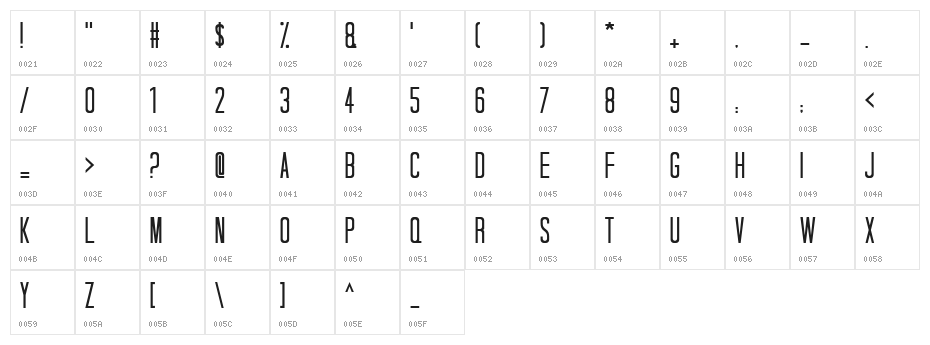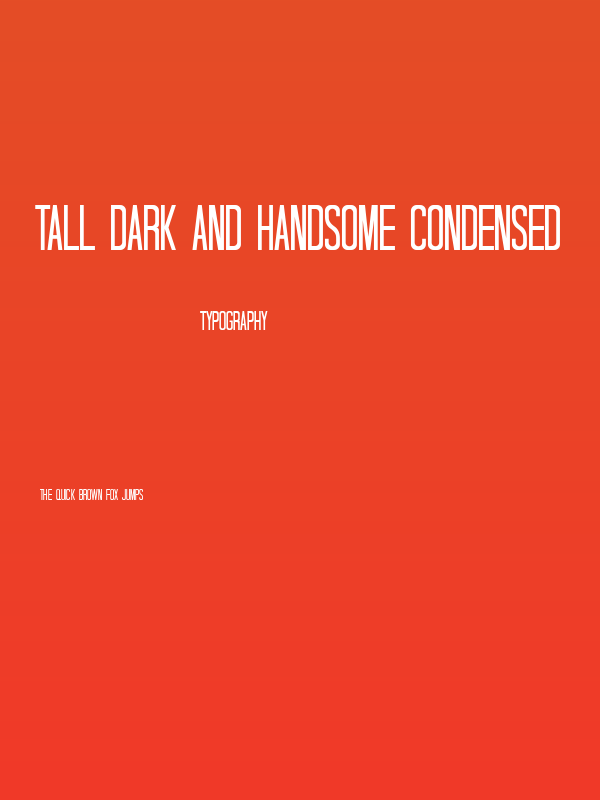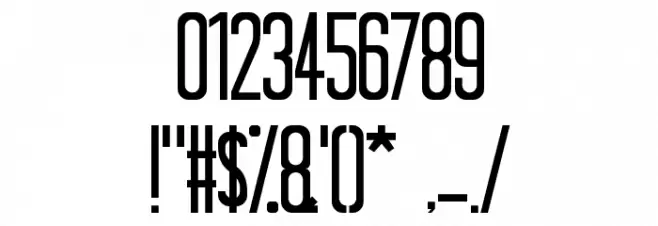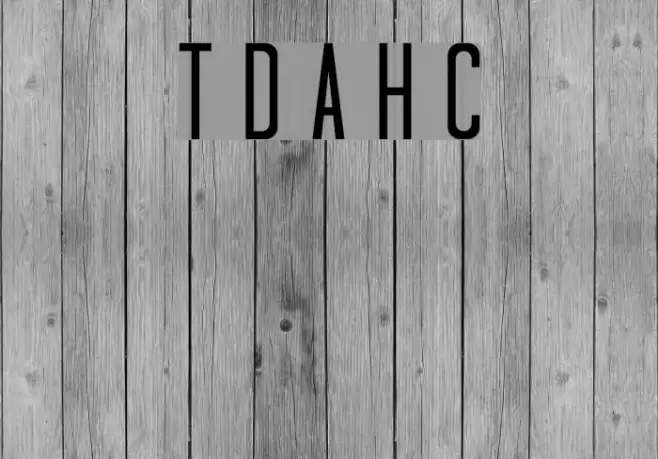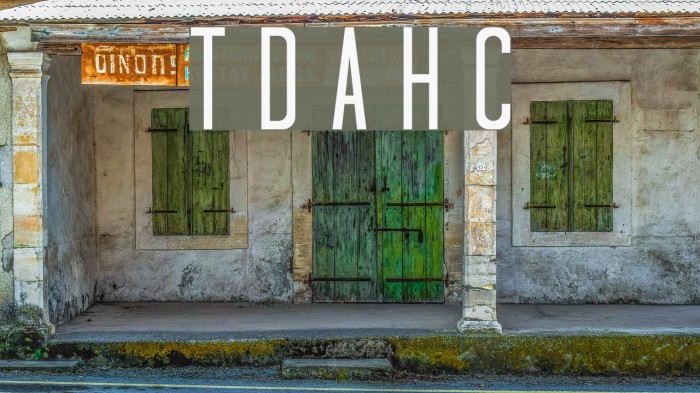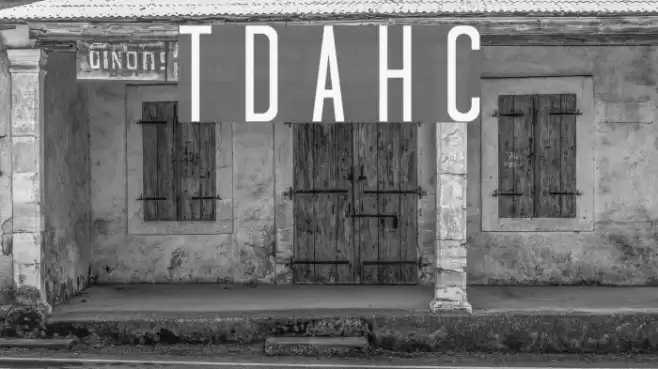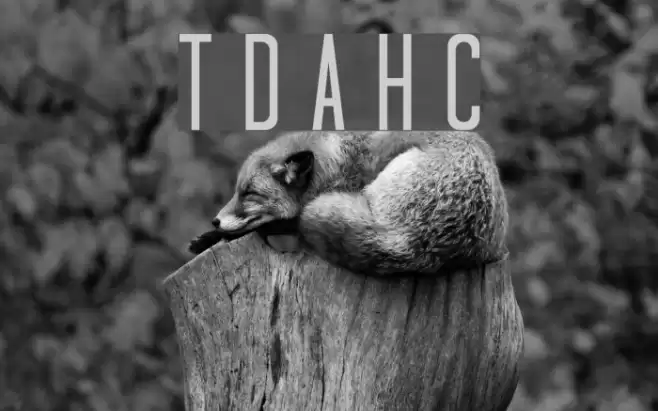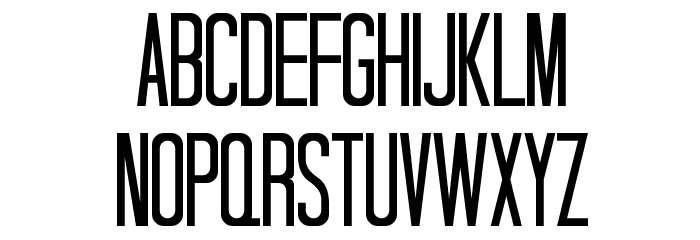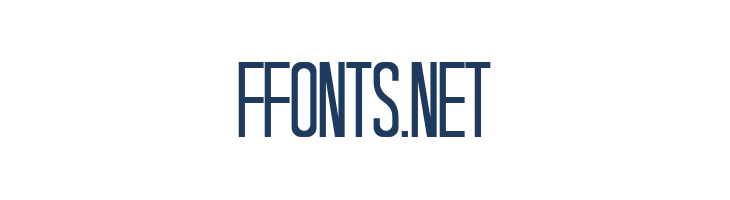
Tall Dark And Handsome Condensed Font
| Nom | Tall Dark And Handsome Condensed |
| Poids | Condensed |
| Projets proposés | Ideal for branding, advertising, posters, and editorial design where a modern and stylish look is desired. |
Tall Dark And Handsome Condensed